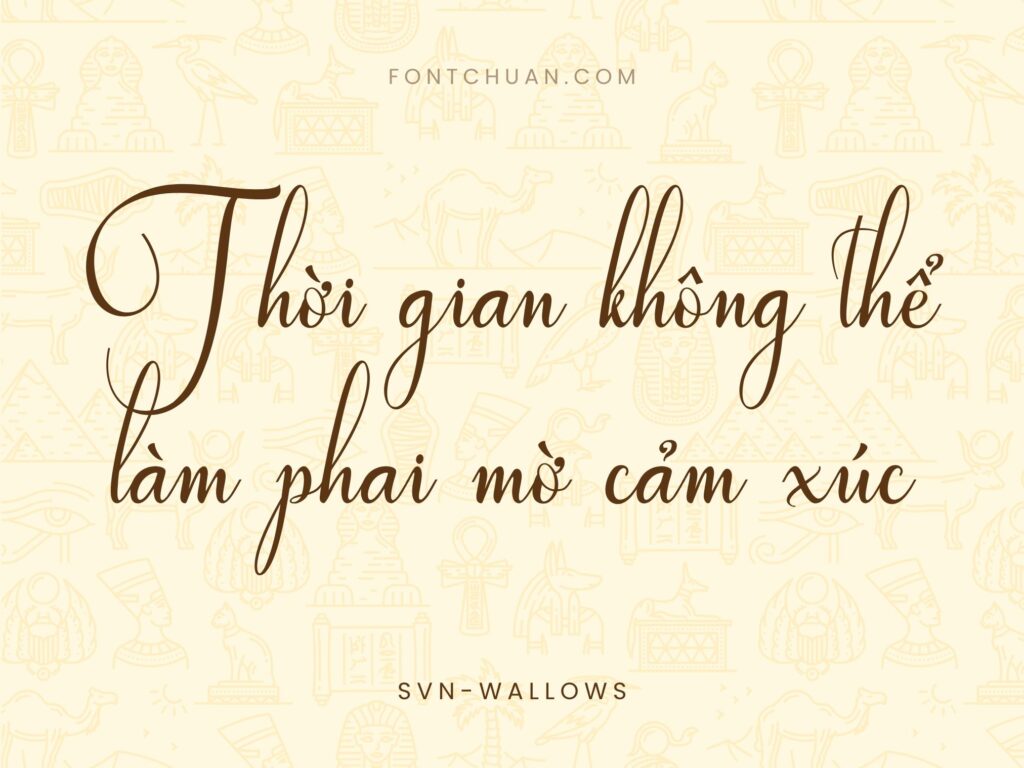
Font SVN Wallows Việt Hóa
Tác giả Font: Ghazi
Font SVN-Wallows là phiên bản Việt hóa của kiểu chữ Wallows, được thực hiện bởi Styleno.1 Fonts. Wallows thuộc nhóm Font Decorative, mang phong cách viết tay tinh tế và thanh lịch, phù hợp cho thiệp mời đám cưới, thiệp chúc mừng, thiết kế tranh vẽ bằng nước, thư từ và nhiều mục đích khác. Font này bao gồm các tính năng như Contextual Alternates, Standard Ligatures, Stylistic Alternates và Stylistic Sets, giúp tăng tính linh hoạt và cá nhân hóa trong thiết kế.
SVN-Wallows lý tưởng cho các dự án yêu cầu sự tinh tế và nghệ thuật, như thiệp mời, tiêu đề, bao bì sản phẩm và các ấn phẩm truyền thông. Các ngành nghề như thiệp cưới, ẩm thực và spa có thể tận dụng font này để tạo điểm nhấn độc đáo trong thiết kế. Ngoài ra, font cũng thích hợp cho các sự kiện như Tết, Valentine, sinh nhật và các lễ hội khác, mang lại vẻ đẹp trang trọng và cuốn hút.